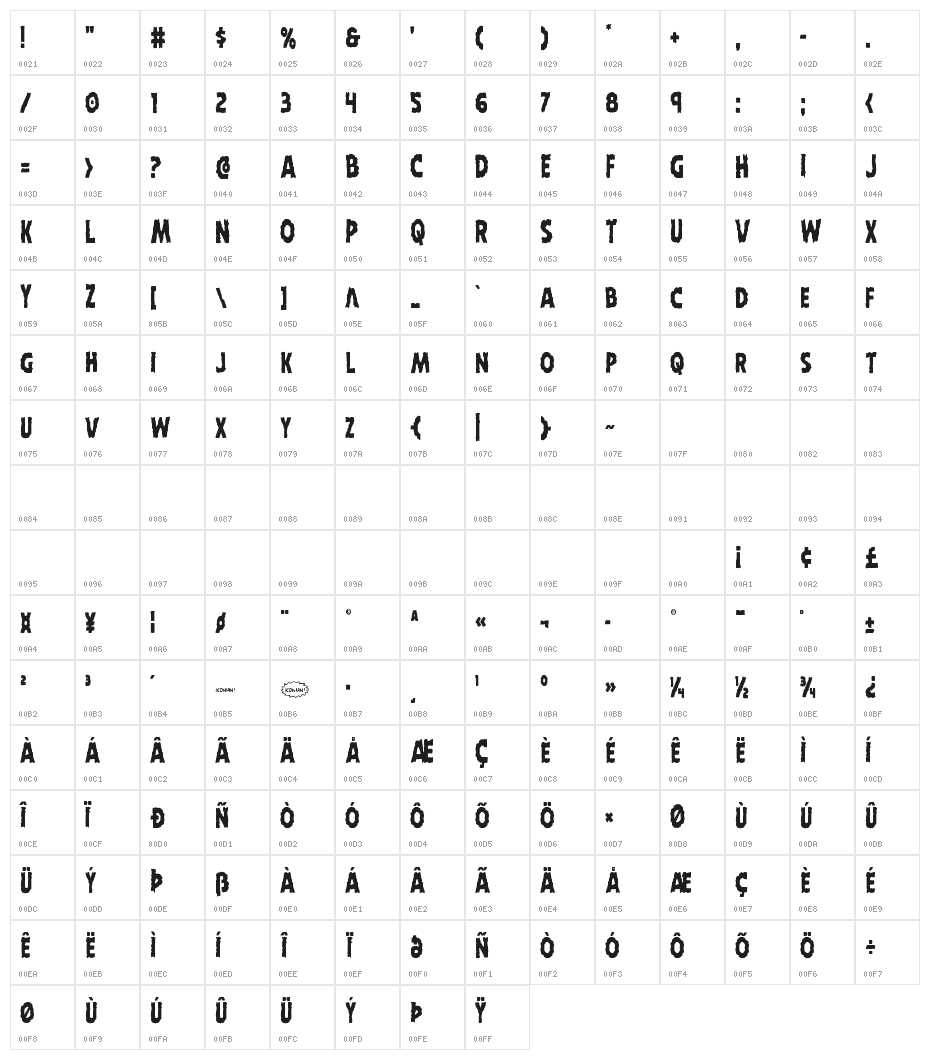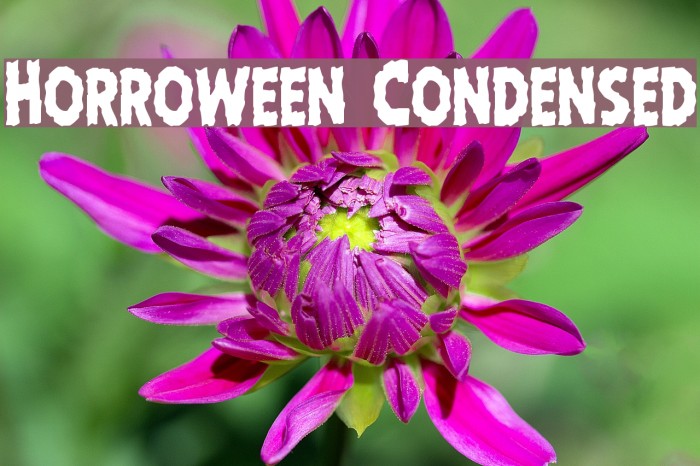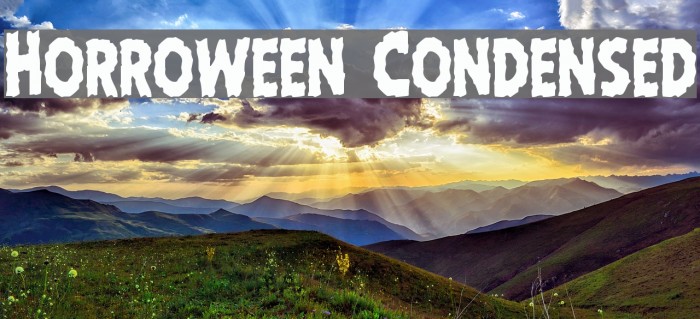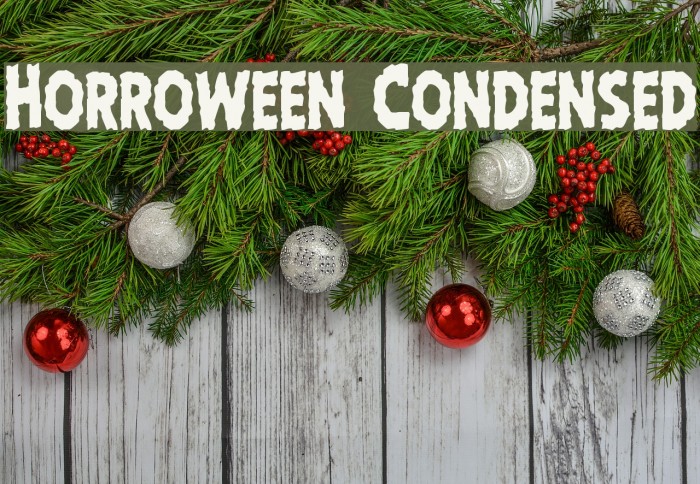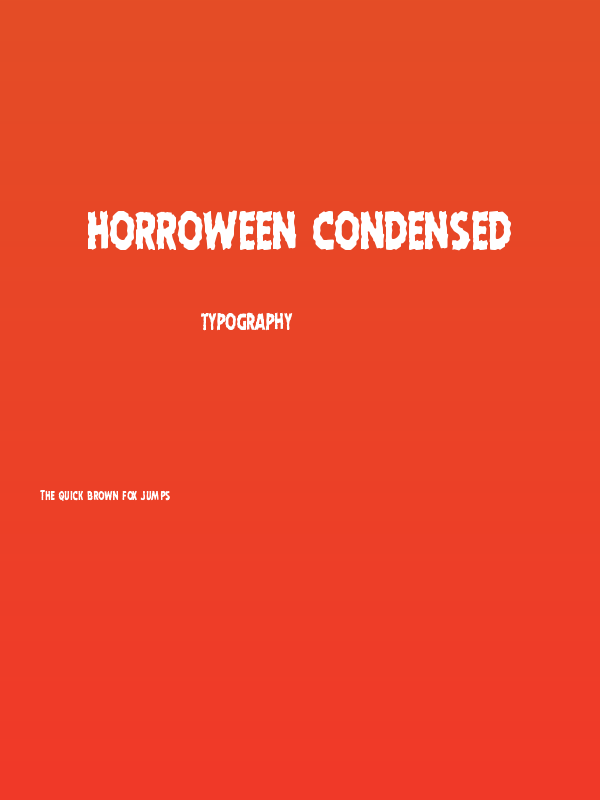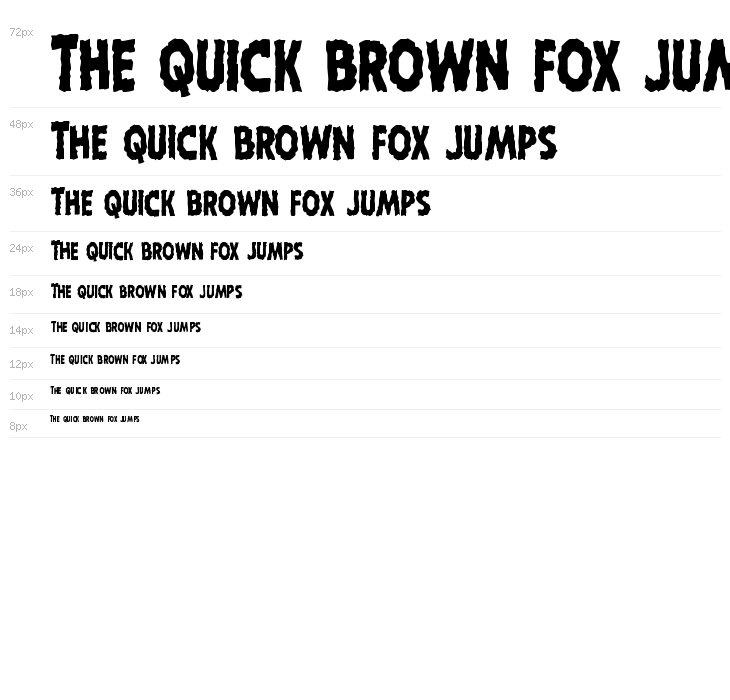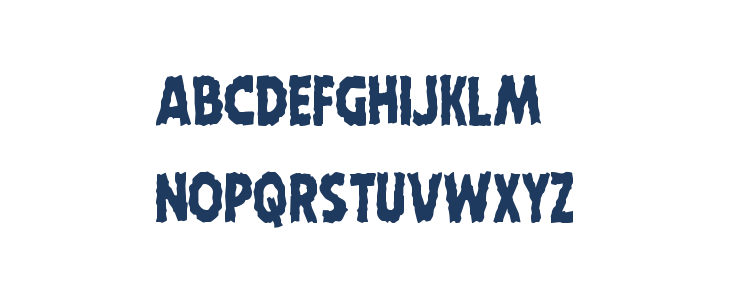
Horroween Condensed Font
| Vorgeschlagene Projekte | Ideal for Halloween posters, horror movie titles, themed party invitations, and spooky event flyers. |